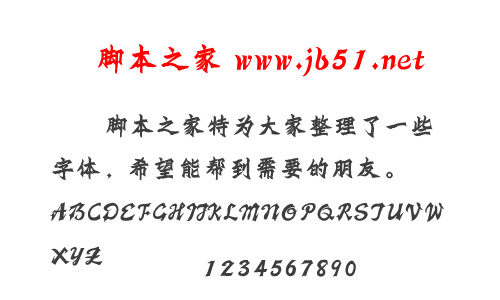
漢儀錦昌體簡(jiǎn)字體是一款具有手寫體風(fēng)格的中文書法字體,該字體蒼勁有力,將古樸之風(fēng)吹進(jìn)新春,字形筆畫寬坦,頓挫波折,棱角分明,有較好的統(tǒng)一性與視覺沖擊力,可以應(yīng)用于廣告設(shè)計(jì)、包裝印刷、產(chǎn)品設(shè)計(jì)、海報(bào)設(shè)計(jì)等方面,歡迎有需要此字體的朋友們前來下載使用。